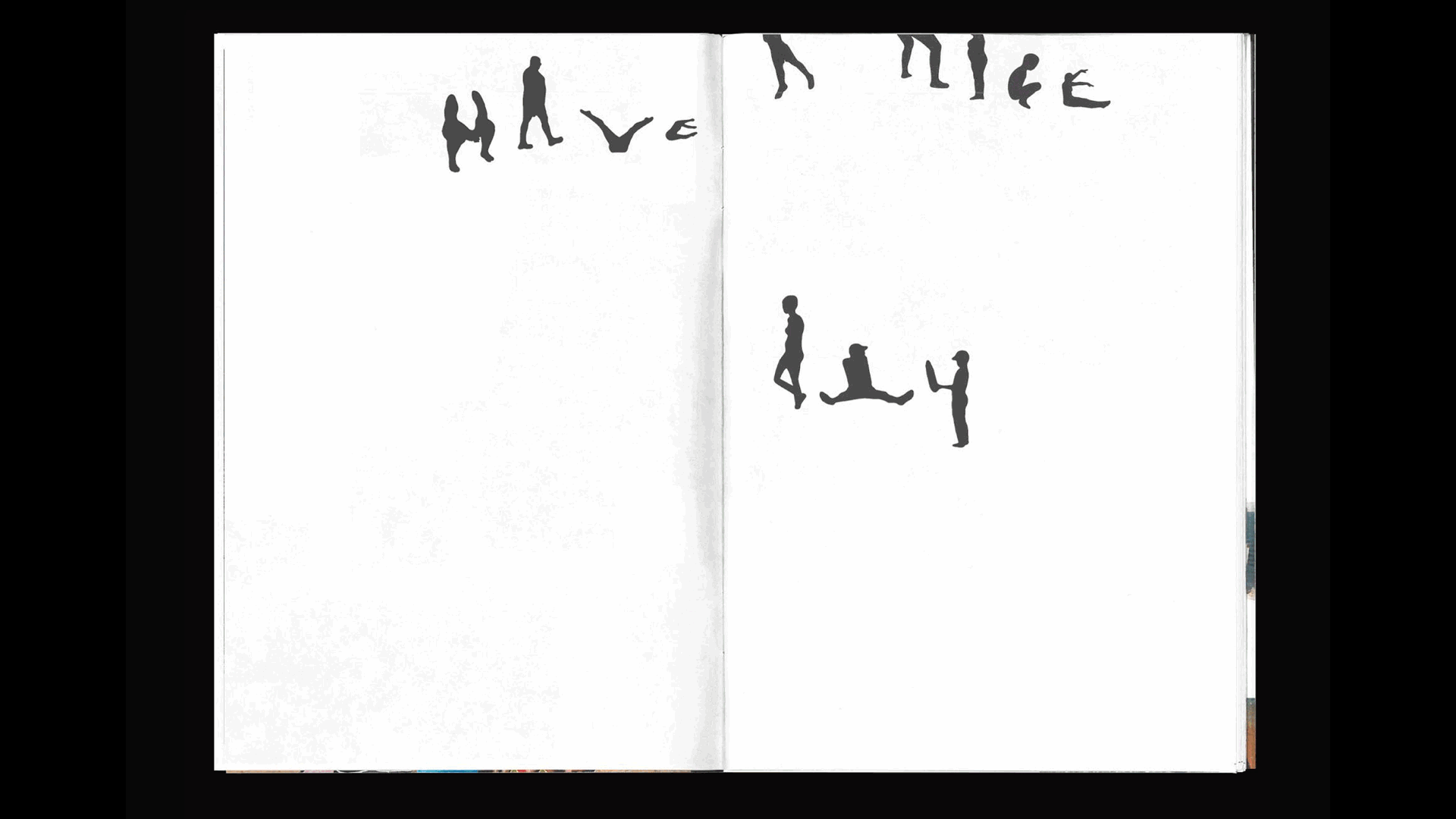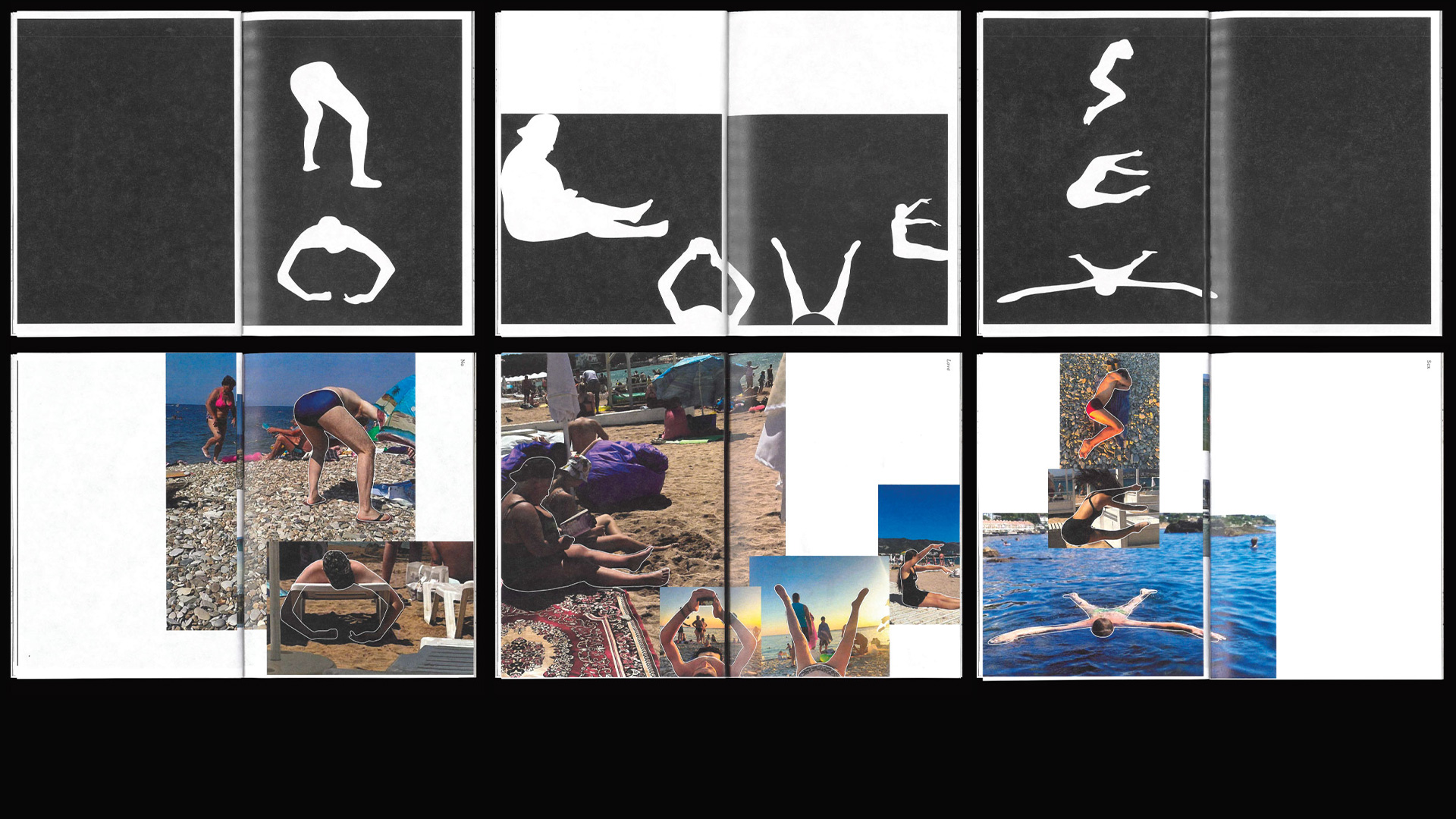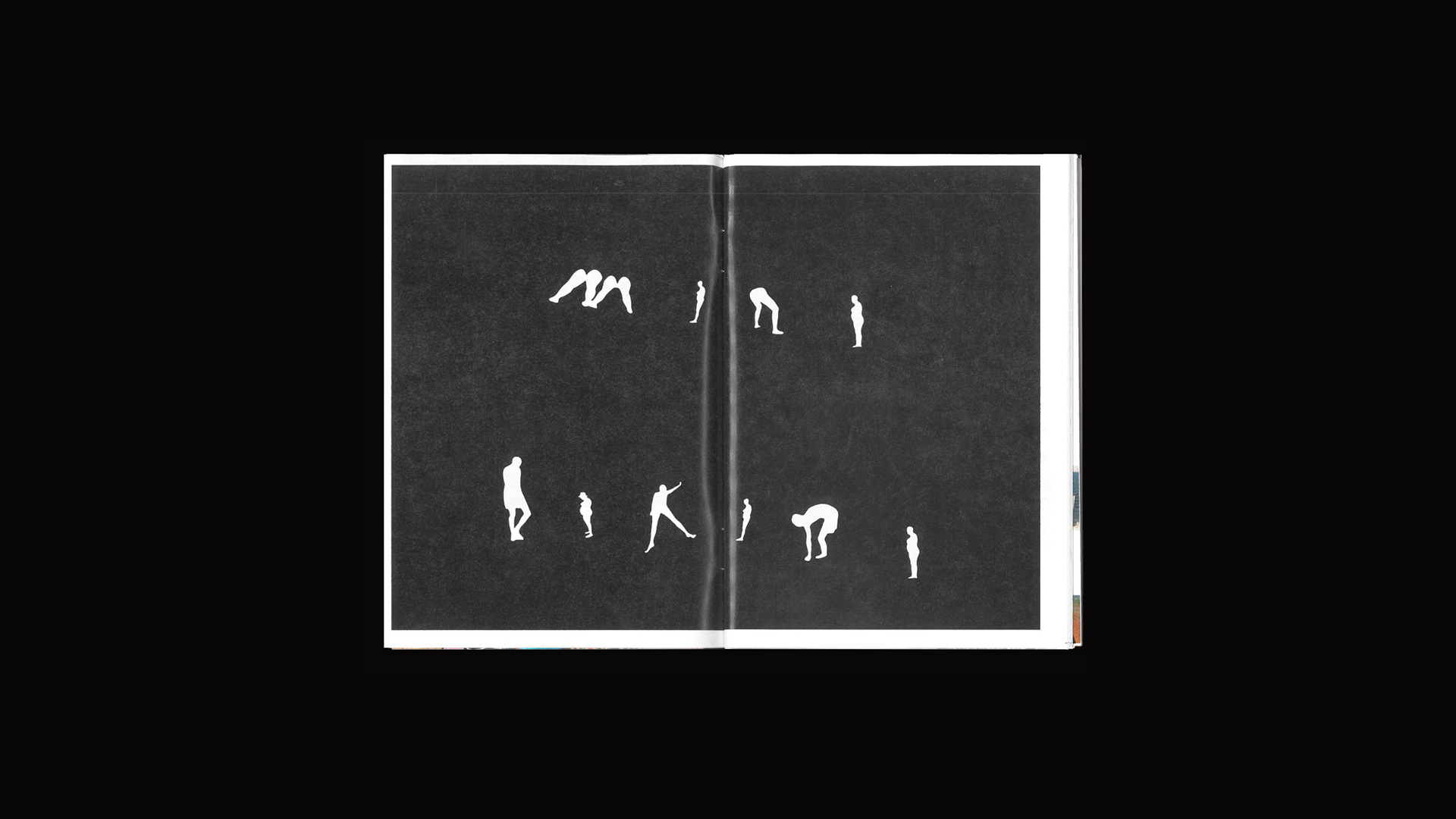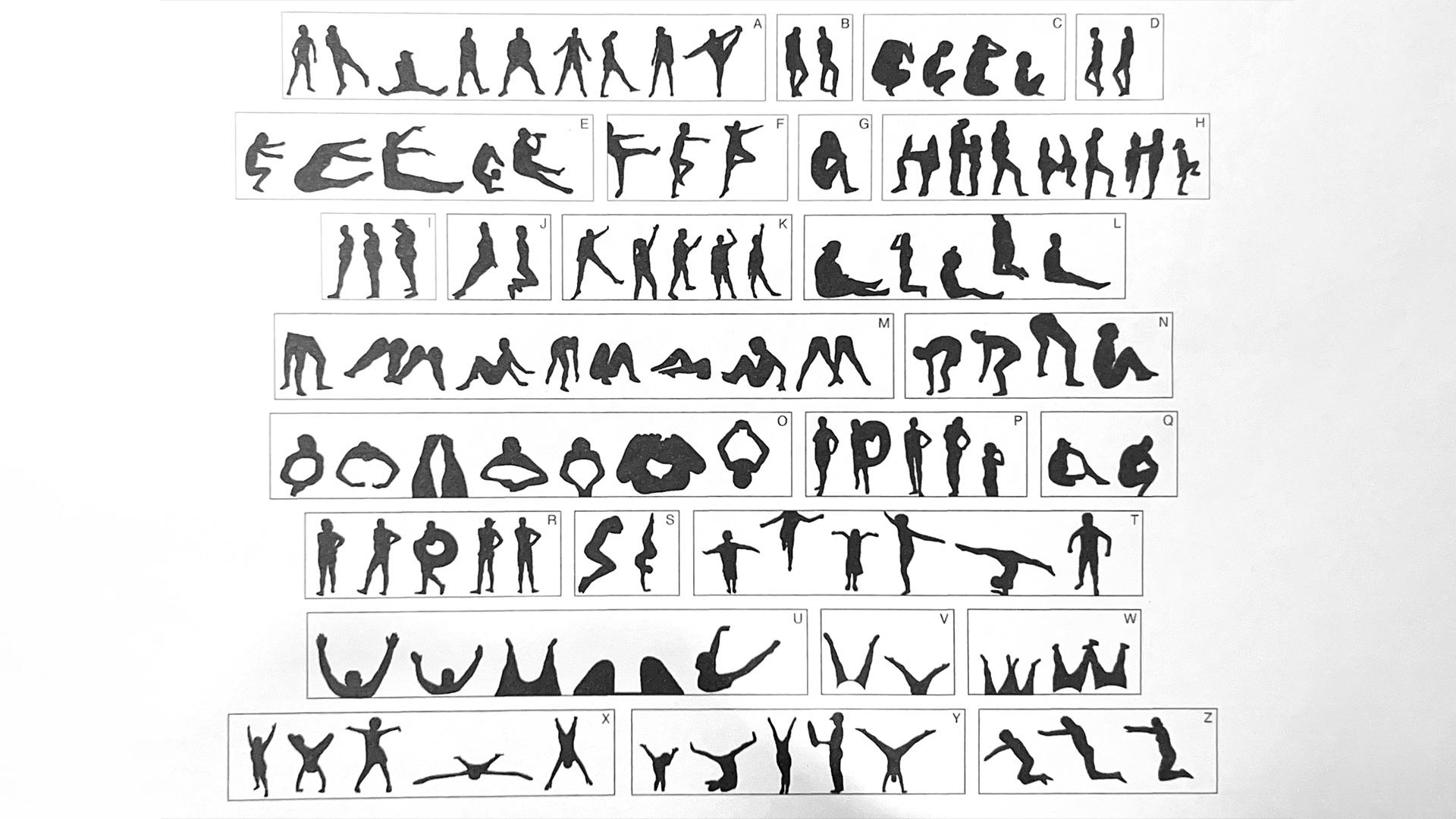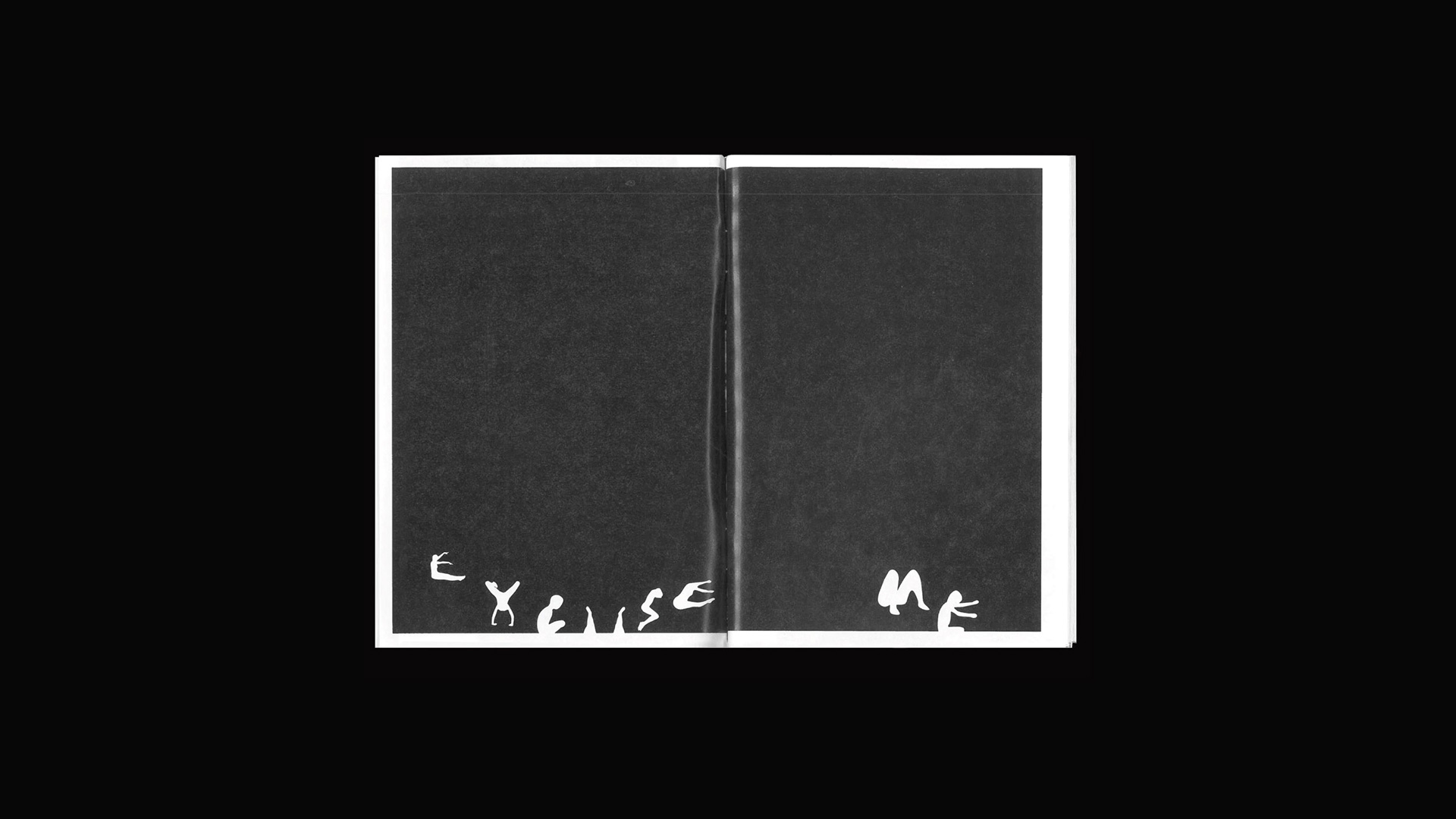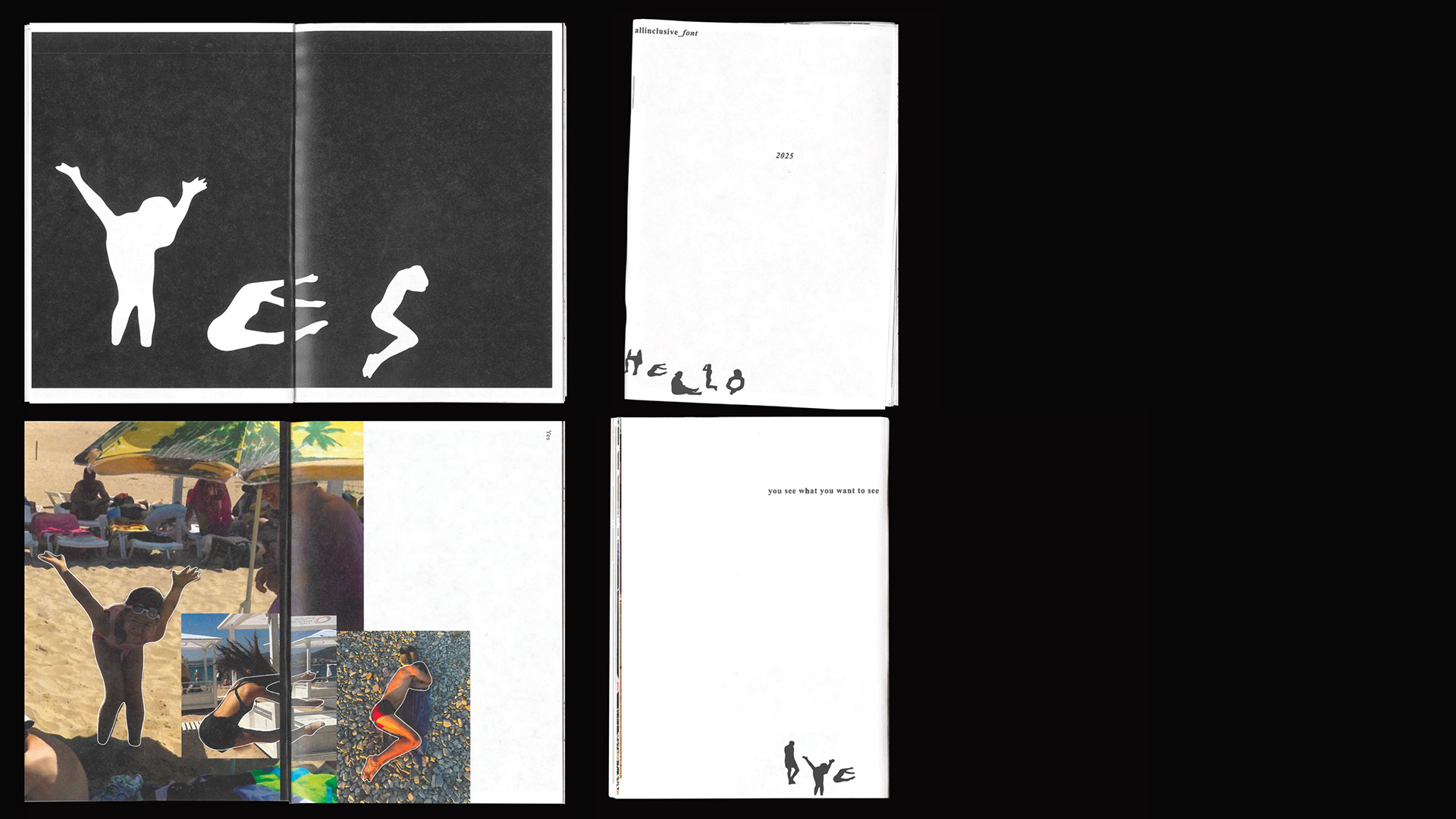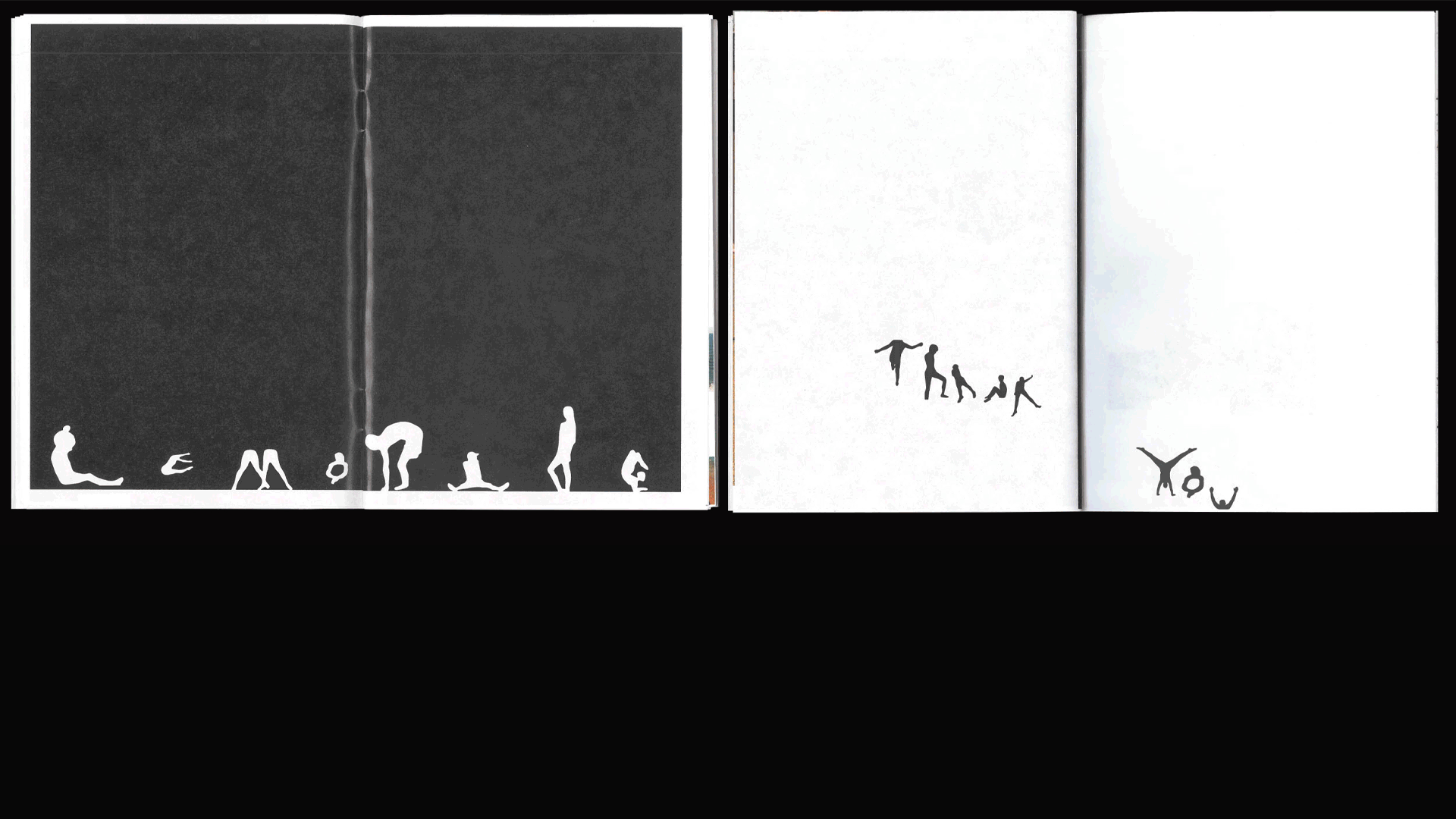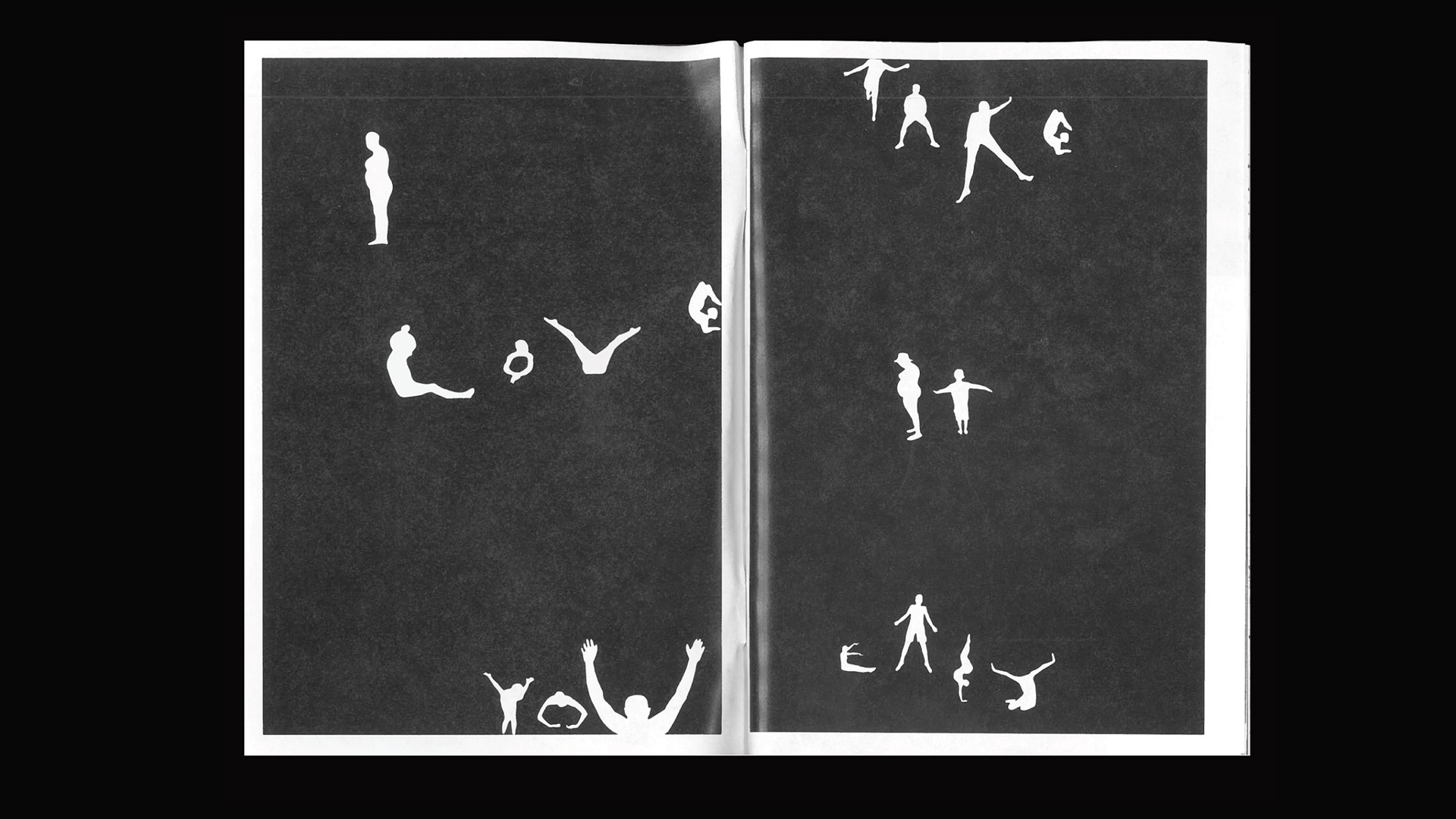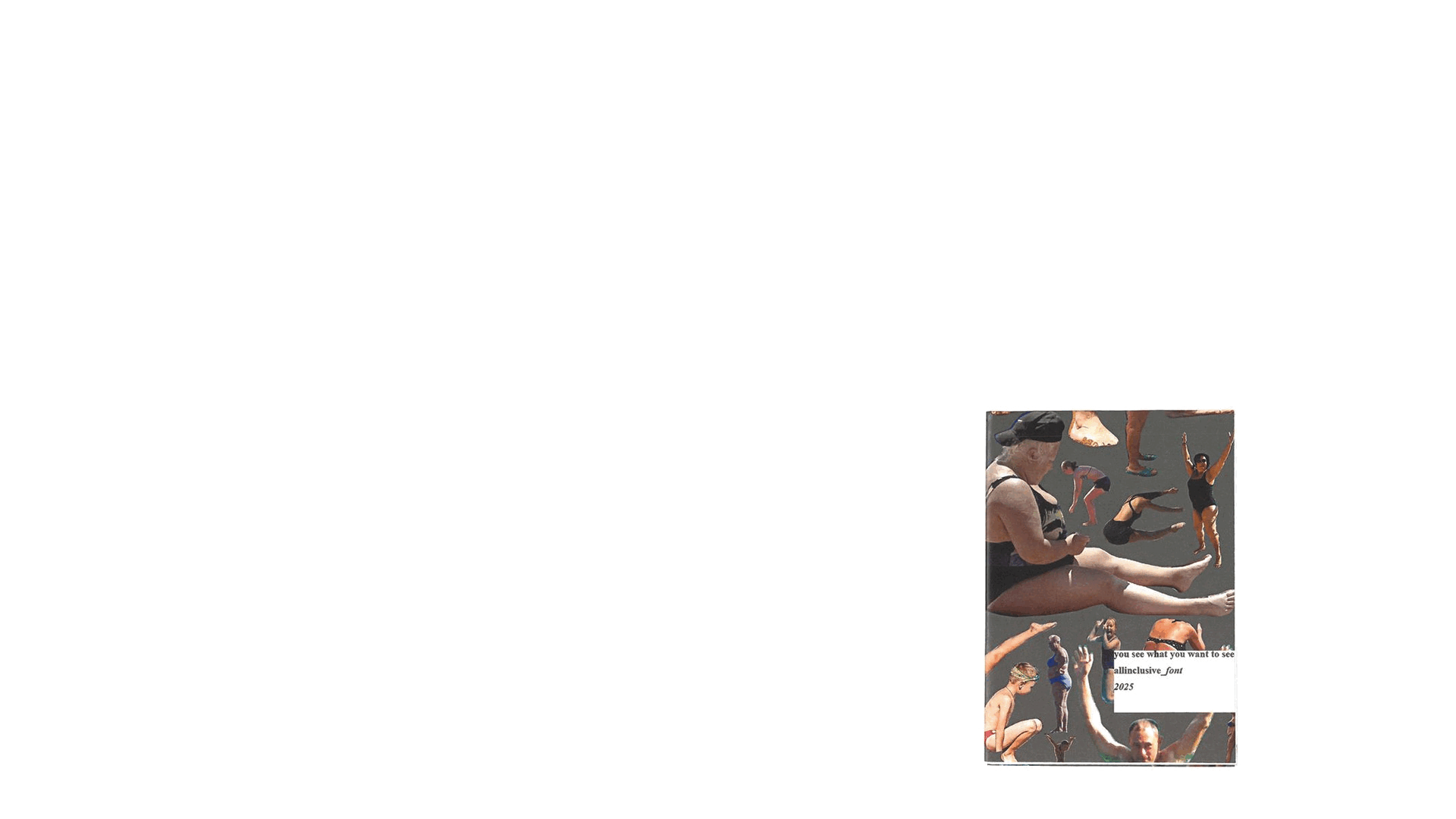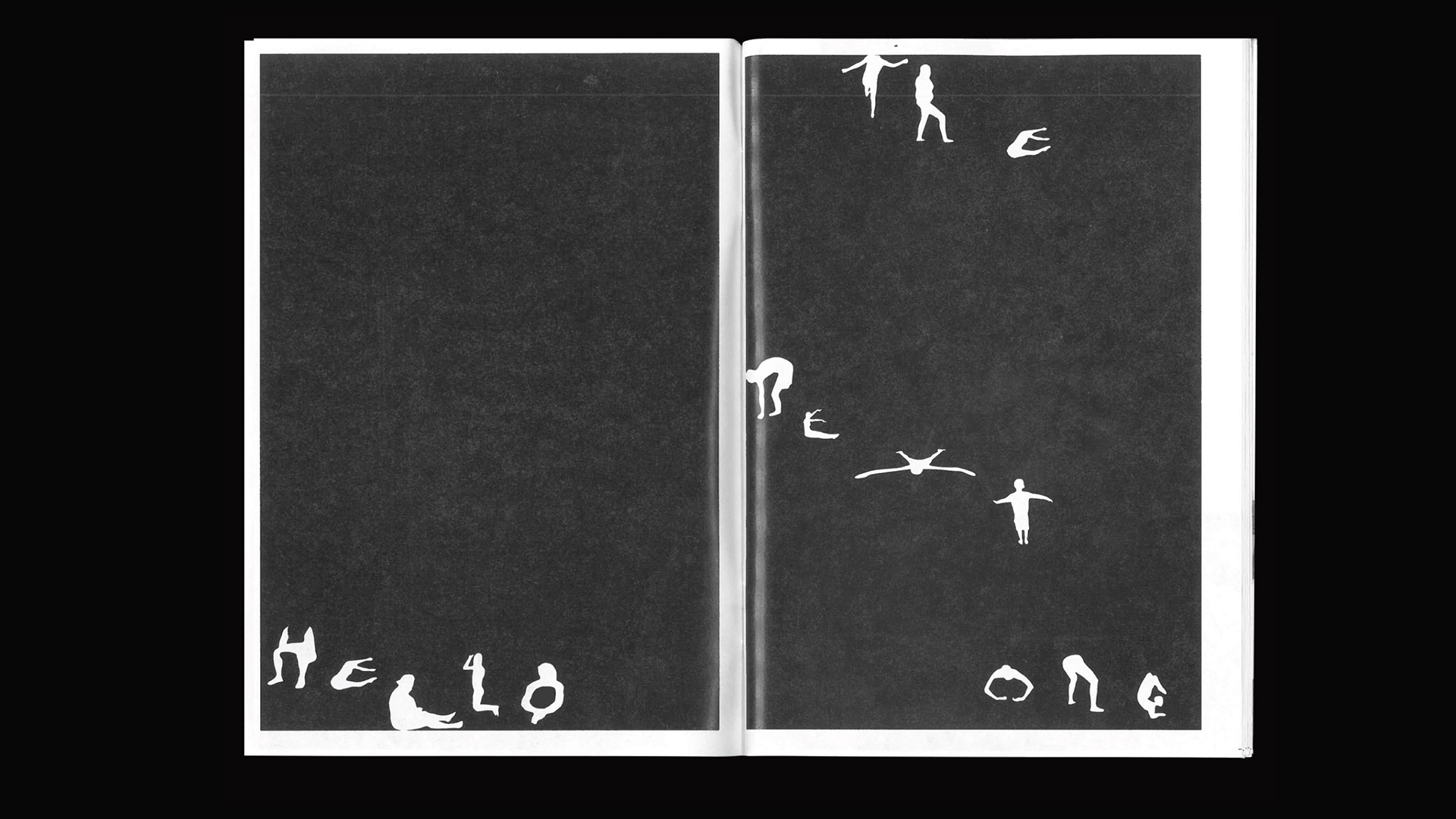
allinclusive
Шрифтовой эксперимент и визуальное исследование о том, как человеческое тело становится носителем языка, не подозревая об этом.
Проект начался за наблюдением и фотографированием случайных людей на пляже: стоящих, лежащих, купающихся и загорающих. Было обнаружено, что в их естественной, ничем не скованной пластике, в их спонтанных жестах и позах, можно прочесть буквы. Случайные тела превращаются в носителей сообщения, которое исходит от множества людей. Так, шаг за шагом возник целый алфавит, не шрифт в традиционном смысле, а скорее архив случайностей, где каждый момент — это уже готовый фрагмент языка, скрытый в повседневности. Многие буквы имеют несколько вариаций, отражая разнообразие тел и множественность форм, в которых язык может проявляться.
Проект allinclusive — одновременно игра и исследование, система и случайность. Это попытка увидеть язык в неочевидном окружении. Он показывает, что язык уже вписан в наши движения, нужно лишь заметить его.